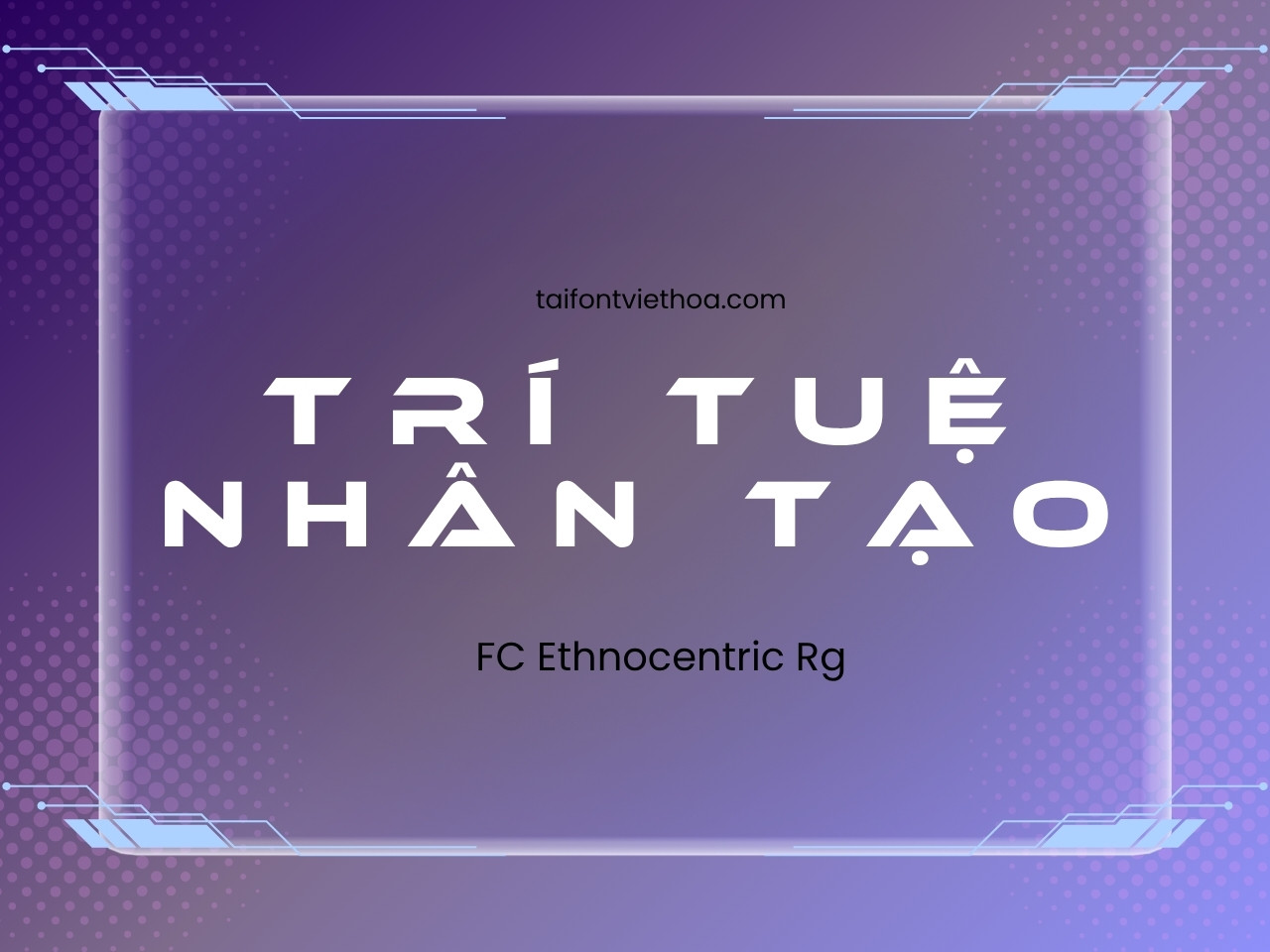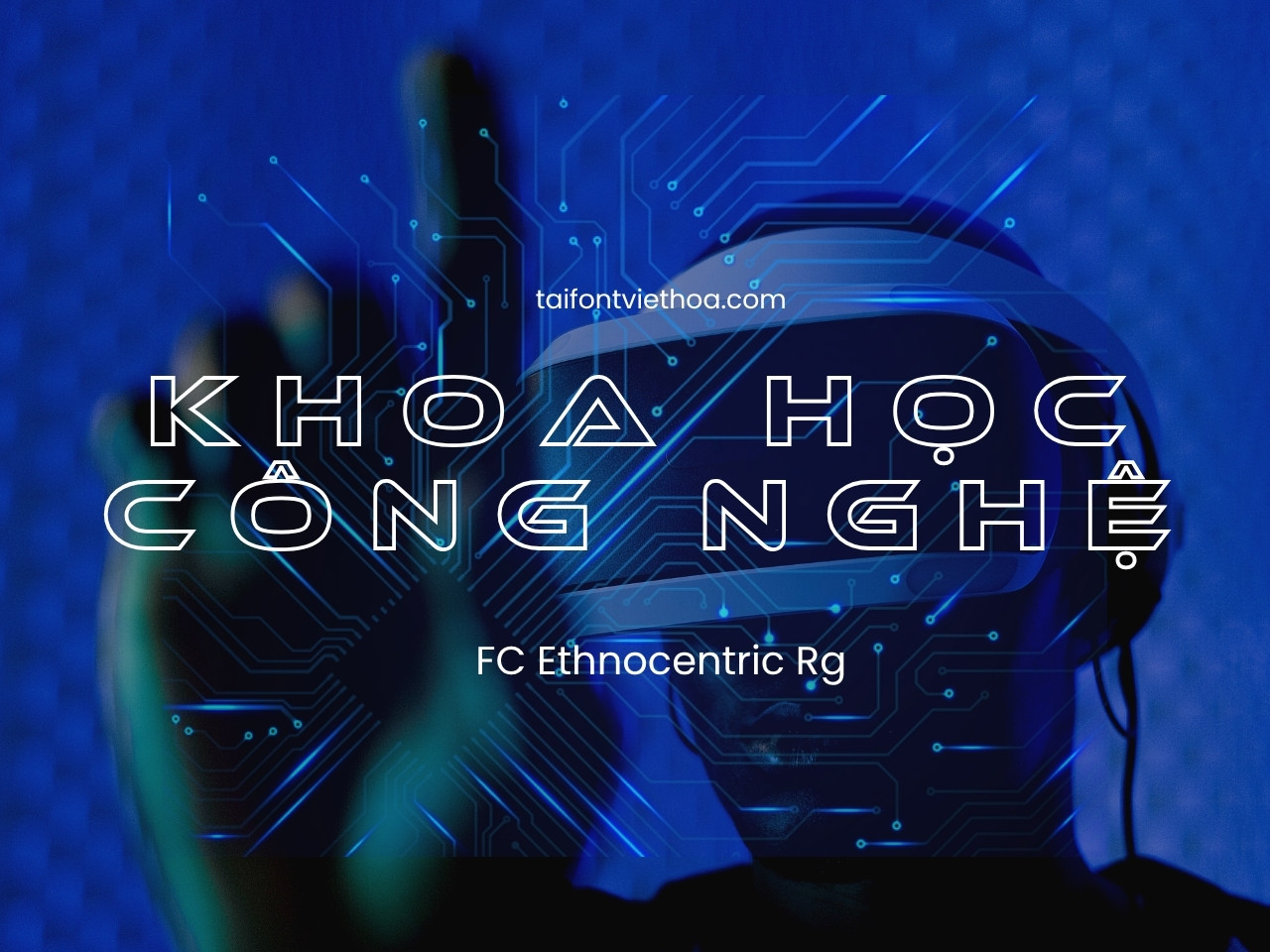
Giới thiệu về font Ethnocentric Rg và bản Việt hóa
FC Ethnocentric Rg là một phiên bản Việt hóa độc lập, được phát triển dựa trên font gốc “Ethnocentric” – thiết kế nổi bật mang đậm phong cách futuristic (tương lai) của nhà thiết kế Raymond Larabie (Typodermic Fonts). Font ban đầu được phát hành rộng rãi trên các nền tảng như Fontspring và Dafont, với cảm hứng đến từ thế giới công nghệ cao, viễn tưởng và các giao diện kỹ thuật số hiện đại. Ethnocentric hỗ trợ bảng Latin mở rộng và hơn 70 ngôn ngữ quốc tế.
Khác với phiên bản “1FTV VIP Ethnocentric Rg” từng được giới thiệu trước đó, FC Ethnocentric Rg là bản Việt hóa riêng biệt, được cộng đồng Font Chuẩn thực hiện và tinh chỉnh tỉ mỉ từng chi tiết. Các dấu tiếng Việt được xử lý hài hòa, tương thích hoàn toàn với bảng mã Unicode mà vẫn giữ trọn chất mạnh mẽ, góc cạnh và hiện đại đặc trưng của font gốc.
Font hiện đã được taifontviethoa.com sưu tầm, kiểm tra và chia sẻ chính thức, giúp giới thiết kế Việt có thêm lựa chọn độc đáo trong các dự án về công nghệ, game, giao diện UI/UX, poster kỹ thuật số hoặc các sản phẩm sáng tạo mang đậm phong cách tương lai.
Đặc điểm thiết kế công nghệ cao và ứng dụng thực tế
FC Ethnocentric Rg mang cấu trúc sans-serif góc cạnh với những đường cắt chéo dứt khoát và các ký tự hình học độc đáo. Các chữ cái được kéo dài chiều ngang, tạo cảm giác tốc độ, chuyển động và hiện đại – rất lý tưởng cho các dự án mang tính sáng tạo cao. Font này còn nổi bật ở khả năng tạo dựng nhận diện mạnh mẽ khi dùng cho tiêu đề, banner hoặc logo.
Ứng dụng lý tưởng của font bao gồm thiết kế thương hiệu công nghệ, dự án AI, giao diện web kỹ thuật số, nhận diện game, esport, poster điện ảnh, banner quảng bá sản phẩm kỹ thuật và các startup công nghệ. Ngoài ra, các ngành nghề như truyền thông kỹ thuật số, phần mềm, sản phẩm sáng tạo hoặc triển lãm tương lai đều có thể tận dụng font này như một tuyên ngôn thị giác đầy mạnh mẽ.